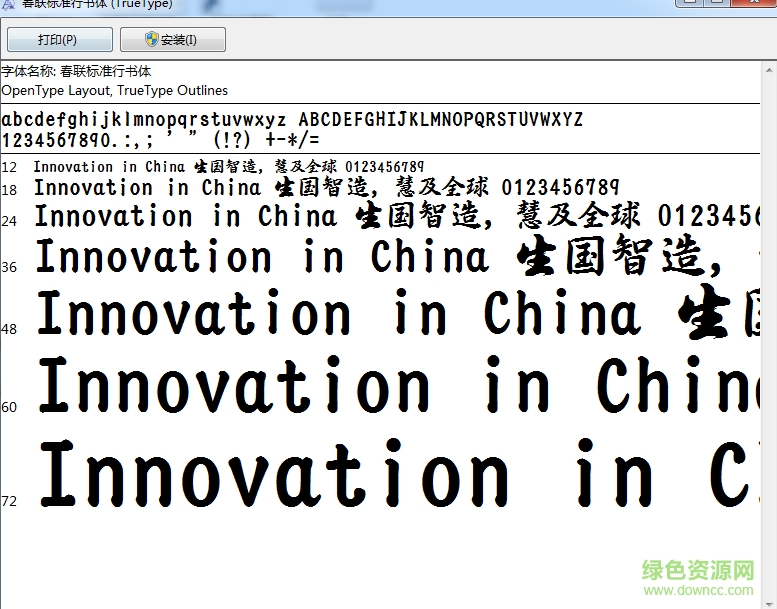
春聯(lián)標(biāo)準(zhǔn)行書(shū)體常用于春聯(lián)、門(mén)聯(lián)等對(duì)聯(lián)的創(chuàng)作和排版中,讓你擁有行書(shū)風(fēng)格的字體設(shè)計(jì),喜歡的朋友快來(lái)綠色資源網(wǎng)下載吧!
春聯(lián)標(biāo)準(zhǔn)行書(shū)體采用標(biāo)準(zhǔn)的行書(shū)字體模板,可用于門(mén)聯(lián)的打印設(shè)計(jì)等。